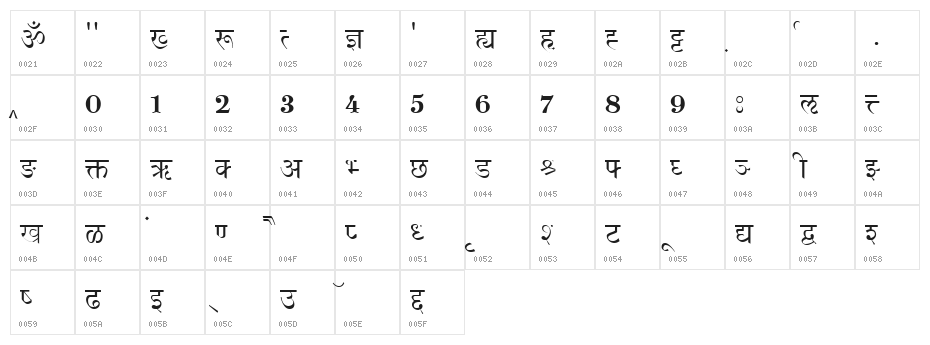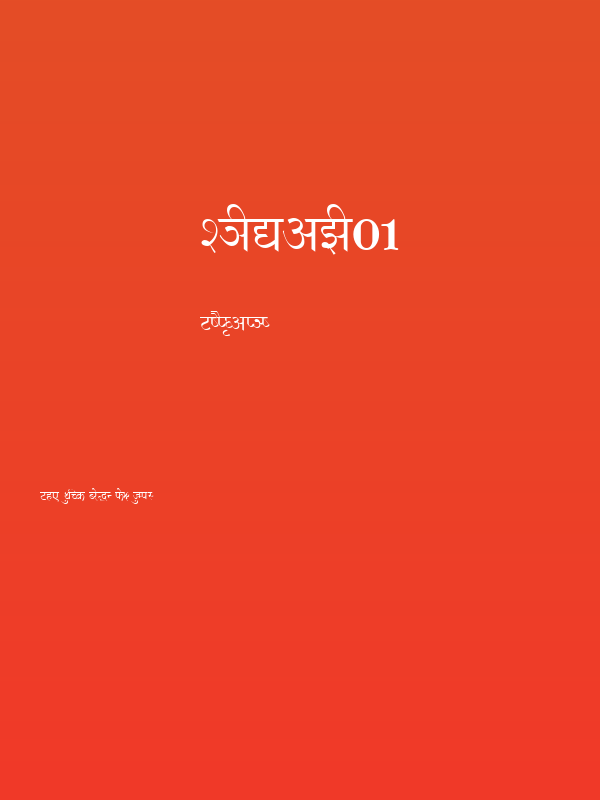
Shivaji01 Font
✎ Hindi
| 整体风格 | Traditional, Cultural |
| 使用场景 | Headlines, Logos, Cultural Texts |
| 推荐项目 | Ideal for cultural publications, traditional event invitations, and heritage branding. |